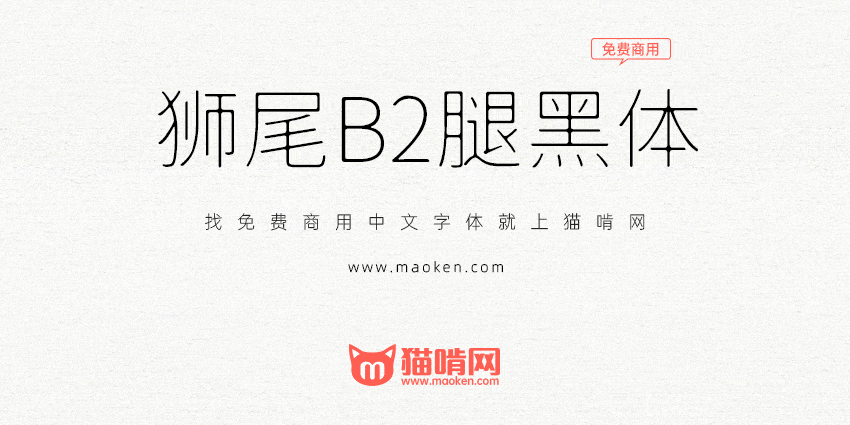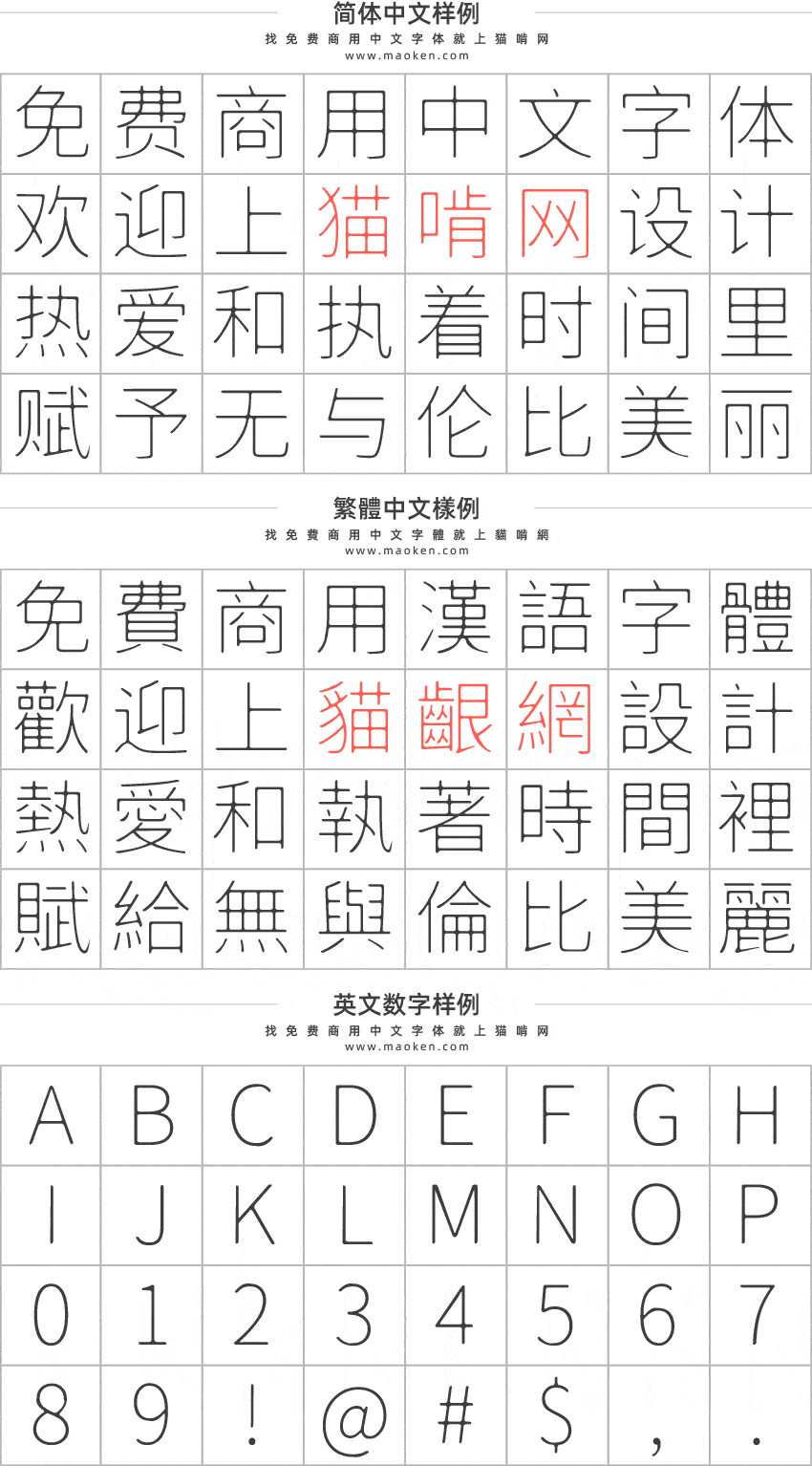
狮尾B2腿黑体基于思源黑体的转角的三角形转成半圆形改造,腿黑指没被拔脚的黑体,彷彿墨晕或是稍微过曝的效果。支援简体中文、繁体中文、韩文与日文;欢迎大家自由应用、自由优化、自由改作!
这款字体设计的非常好,就是有个别字没有改变。比如“拔”这个字
稍有不同~
诶嘿,有些字体还是改的不错的。挺喜欢改圆弧的那些,有晕墨的感觉,siwei宋体
这个狮尾b2黑体不是一模一样吗
稍有不同~
吐舌(ૢ˃ꌂ˂ૢ)!真没看出来,还比对下圆的弧度都差不多!我觉得肉眼看不太出来吧
很明显,B2黑体没有脚,B2腿黑体有脚,并且B2腿黑体有国标版,而B2黑体只有台标
哦哦哦,主要是脚的分别啊,(*/ω\*)捂脸,我都没注意到他的脚,只是看整体效果就是圆弧,请教一下他的脚指的是哪里?呜呜,虚心请教